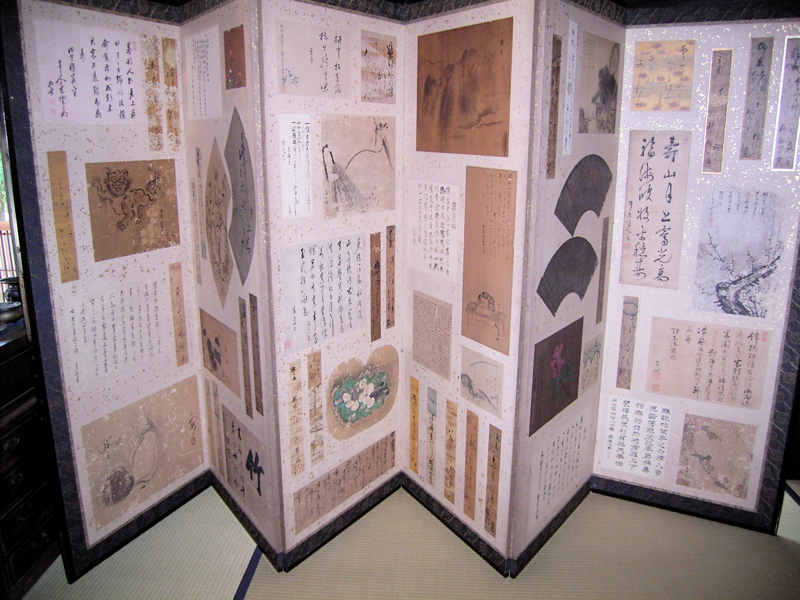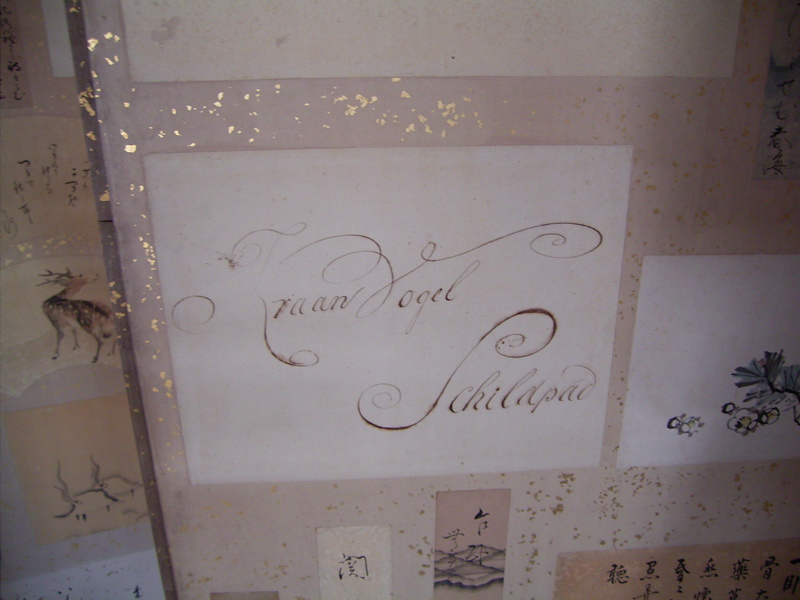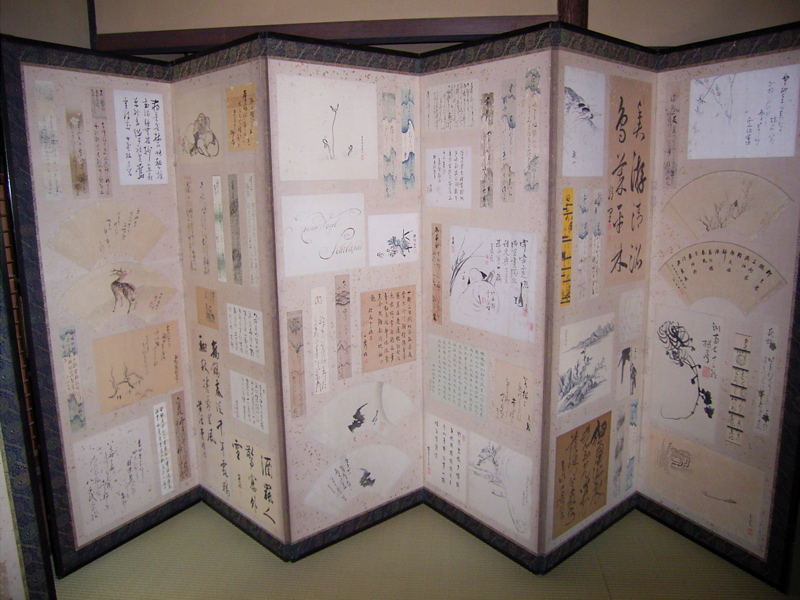
貼りまぜ屏風
昨年の夏の話です。
九州のとある民家に泊めてもらった日、そこの女主人にその家の家宝を見せてもらいました。貼り交ぜ屏風1双です。
貼り交ぜ屏風とは、色紙・短冊・書簡等をとりまぜて屏風に貼りあわせたものです。たくさんの書画を貼り合わせて作った華やかなふすまや屏風のことで、その貼る位置は屏風を作る表具師
のセンスによってレイアウトされます。
この屏風は女主人が、以前ある骨董屋さんで出会って一目で気に入り、清水の舞台から飛び降りる決意で購入したのだそうです。やったね〜!
一つ一つが本当に面白いので、ながめていて飽きません。長い時間をかけてゆっくり鑑賞させてもらいました。素晴らしい時間でした。
その貼りまぜの中にこんなのもあったのです。
蛇口の鳥亀?
これを屏風に貼っちまえ、と思ったこの所有者。いいぞ!このセンス。そしてちゃんと上下たてよこ間違わずに貼った表具師さんもエライ!
九州前原にある、かの銀河荘に行って女主人にお願いすると見せてもらえるかもしれませんよ〜。